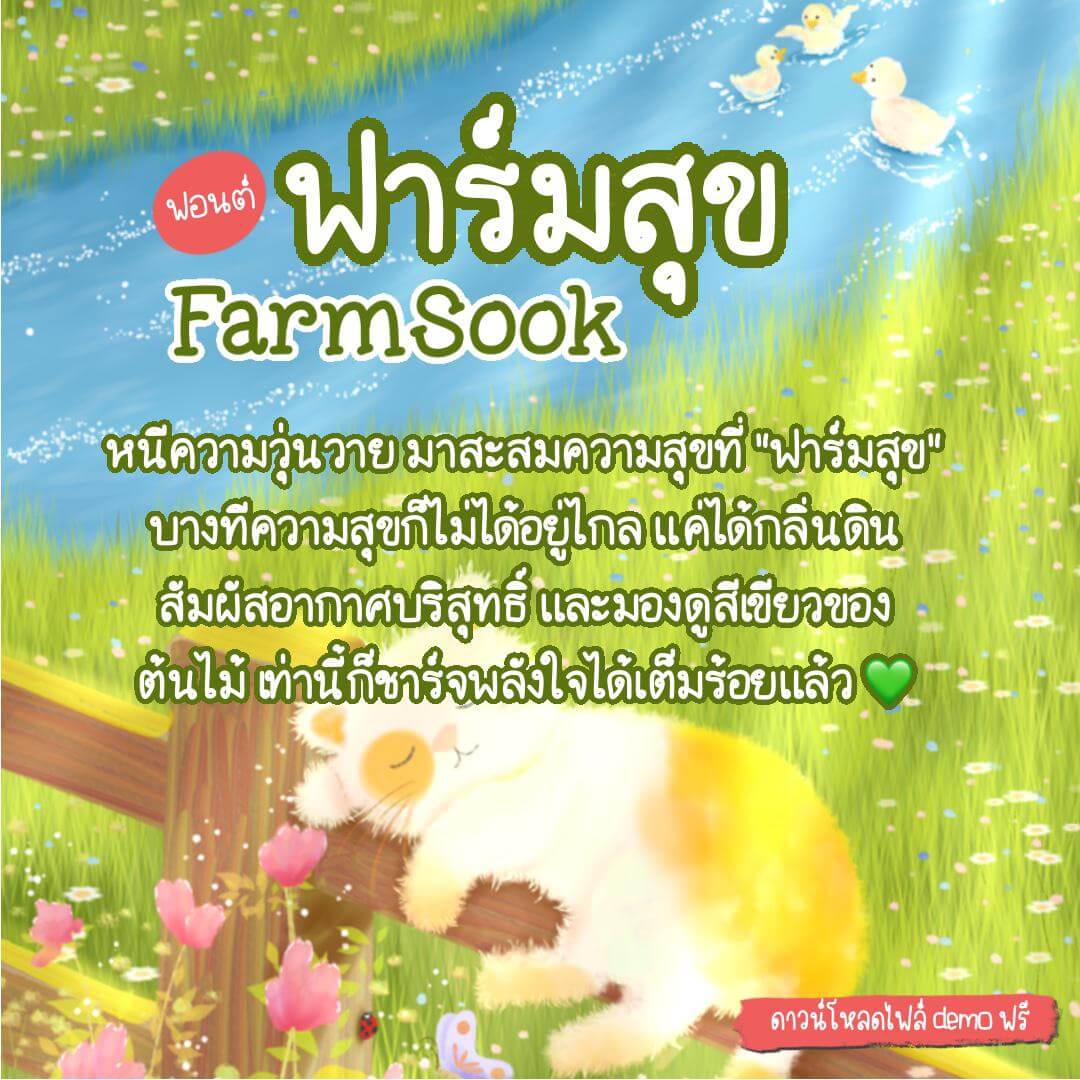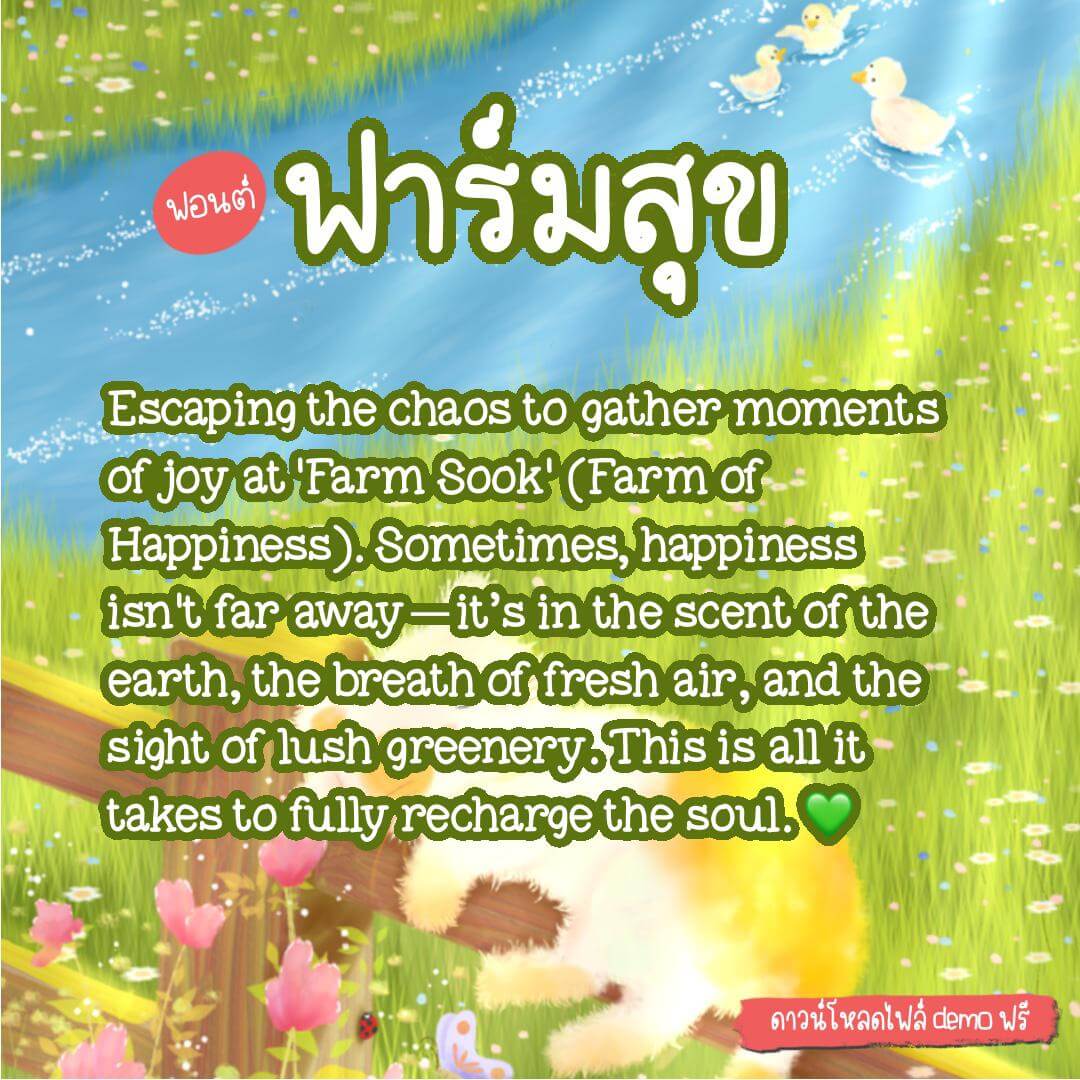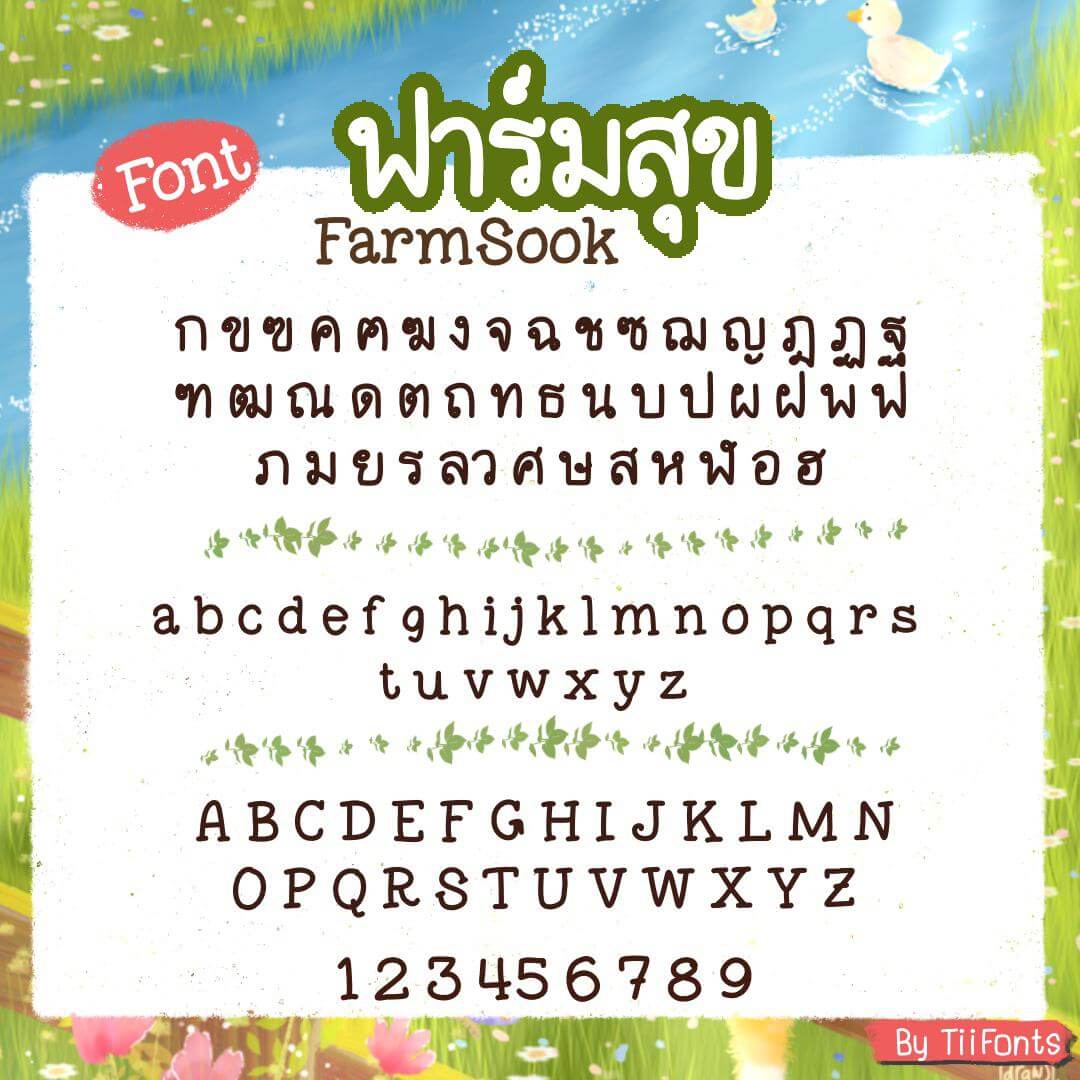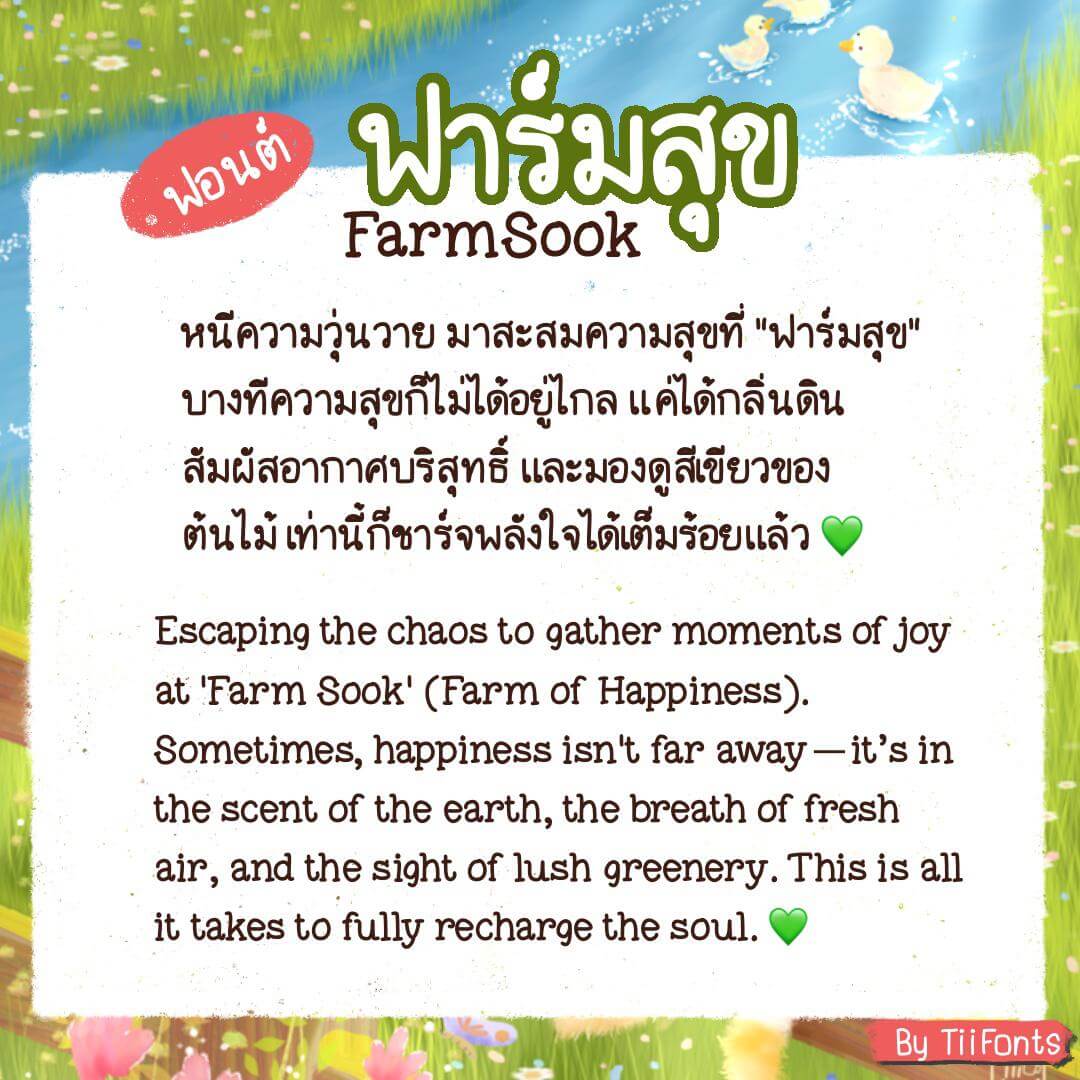
เติมความละมุนให้ทุกงานออกแบบ หนีความวุ่นวาย มาเติมความสดใสด้วยฟอนต์ “ฟาร์มสุข” ฟอนต์ลายมือนุ่มนวล เป็นกันเอง เหมือนได้พักผ่อนท่ามกลางธรรมชาติ
บุคลิกของฟอนต์:
• ละมุนตา: เส้นสายเป็นระเบียบแต่มีความโค้งมน อ่านง่าย ไม่แข็งกระด้าง
• อบอุ่น: ให้ความรู้สึกเหมือนเขียนด้วยมืออย่างตั้งใจ เพิ่มความเป็นกันเองให้กับชิ้นงาน
• โมเดิร์นแต่คลาสสิก: เข้าได้กับทุกสไตล์ ไม่ว่าจะเป็นสายมินิมัล หรือสายกราฟิกสีสันสดใส
ฟอนต์นี้เหมาะกับงานแบบไหน?
• สาย Content: ทำสรุปความรู้ เขียนแคปชันลงรูปใน IG/Facebook ให้ดูซอฟต์และน่าอ่าน
• สาย Cafe & Handmade: ออกแบบเมนูอาหาร ป้ายสินค้า หรือการ์ดขอบคุณลูกค้า
• สาย Vlog: ใช้ทำซับไตเติล หรือหัวข้อวิดีโอแนวไลฟ์สไตล์ เที่ยวธรรมชาติ หรือทำอาหาร
• Digital Planning: จดโน้ตใน Goodnotes ให้ดูเป็นระเบียบและน่ารัก